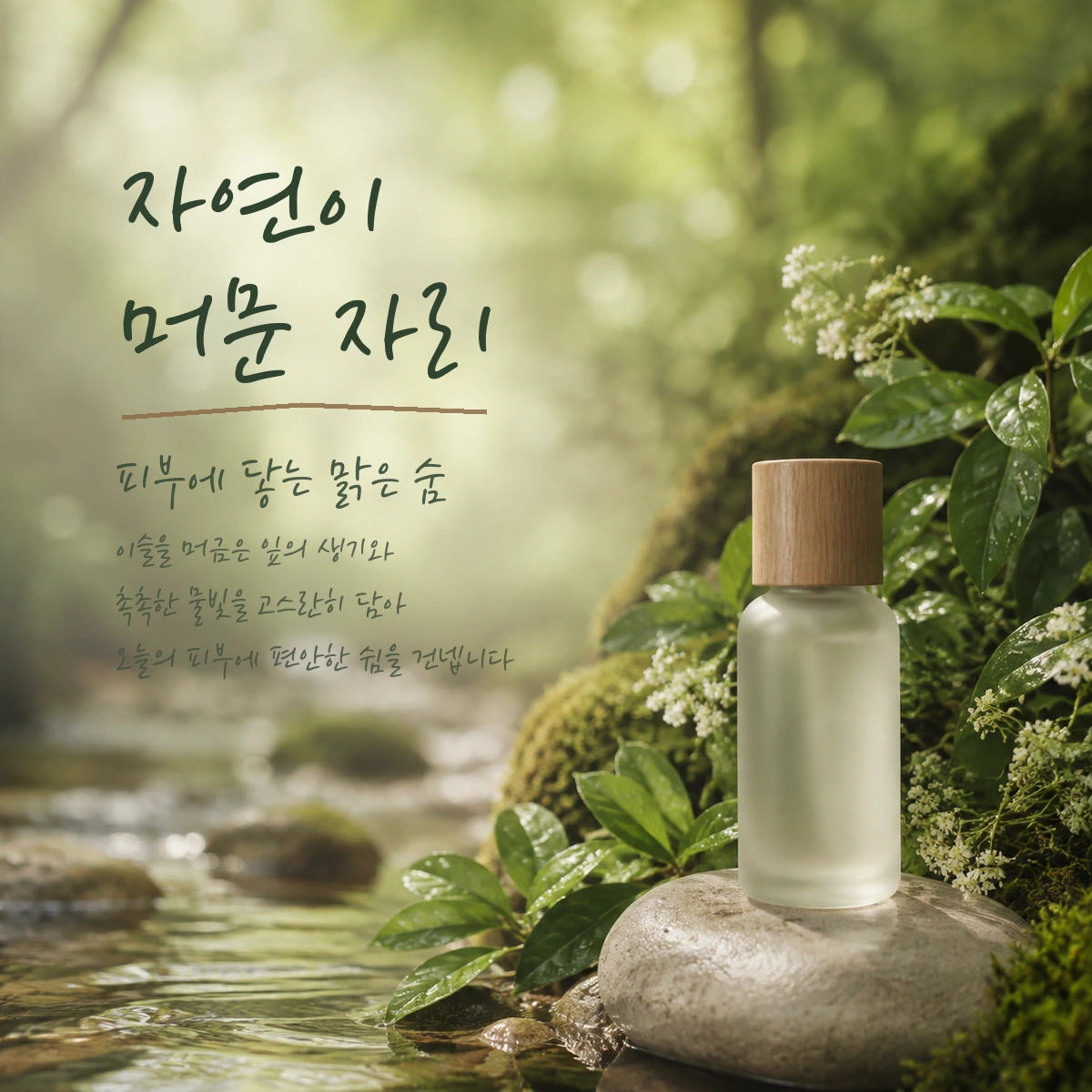
잉크립퀴드 — 더페이스샵에서 배포하는 무료 폰트입니다. 잉크가 번지듯 유연한 획과 자연스러운 필압을 살린 감성적인 펜글씨체
더페이스샵이 2015년에 내놓은 서체로, 윤디자인연구소의 박수진 디자이너가 만들었습니다. 기업 전용서체가 아니라 **단일 제품을 위한 서체**라는 점이 이례적입니다. 잉크 립퀴드라는 립 제품 출시에 맞춰 개발했고, 제품을 산 사람에게 서체를 주는 프로모션이 기획 단계부터 함께 짜여 있었습니다.
조형이 제품의 성질을 따라갑니다. 만년필로 쓴 듯한 캘리그래피 기반인데, 자유로운 획 방향과 변화하는 획 굵기로 촉촉한 느낌을 표현했습니다. 롱래스팅 글로시 리퀴드 립스틱이라는 제품의 특징을 글자의 물기로 옮긴 셈입니다. 라틴은 곡선을 강조하고 S와 R, e, g 같은 글자에 오픈타입 대체자를 넣어 붓의 표현력을 살렸습니다. 딩벳 10종도 함께 들어 있습니다.
굵기는 하나입니다. 제품 출시 일정에 맞추느라 제작 기간이 촉박했다고 알려져 있습니다. 파일에서 재어 보면 획이 매우 가늘어 자면을 채우는 비율이 낮으니, 작은 크기나 복잡한 배경에서는 묻히기 쉽습니다. 크게 쓰세요.